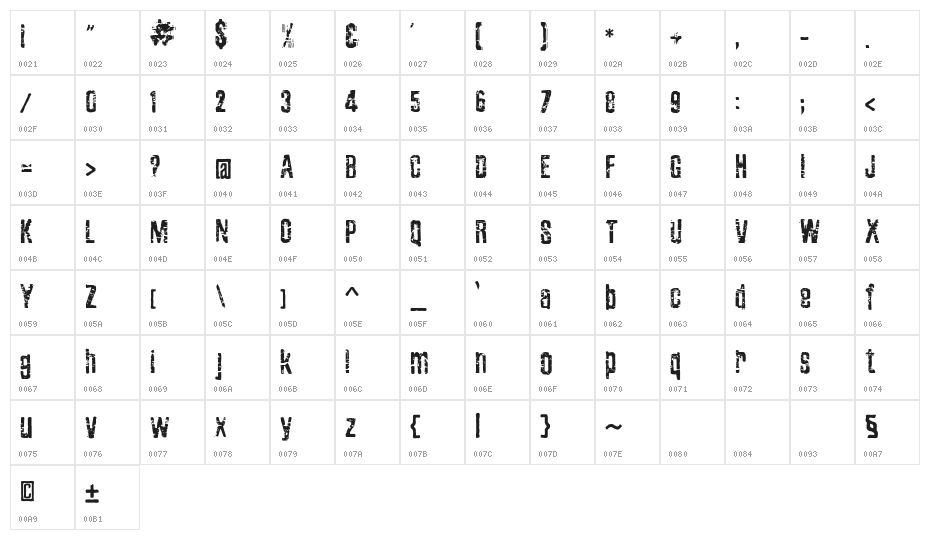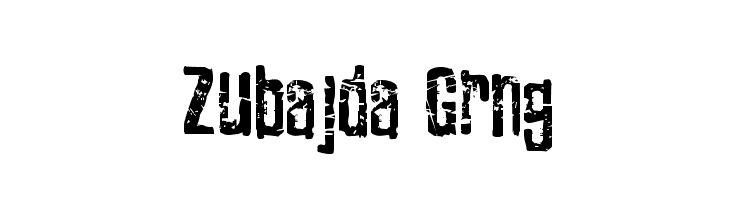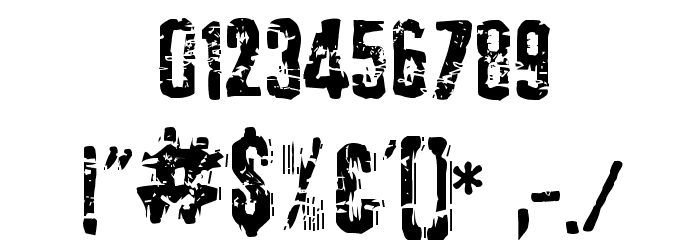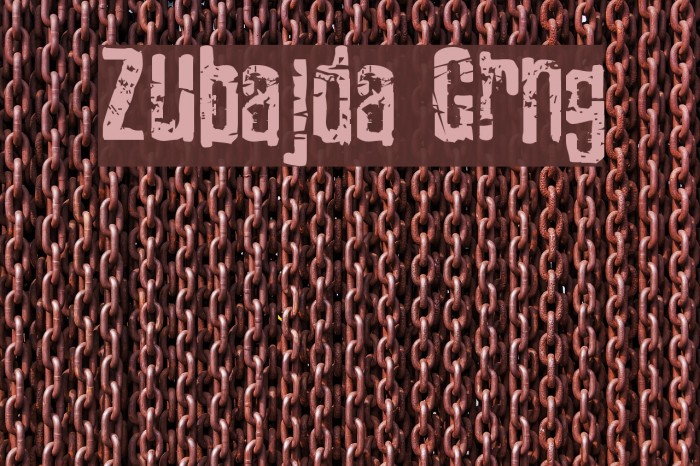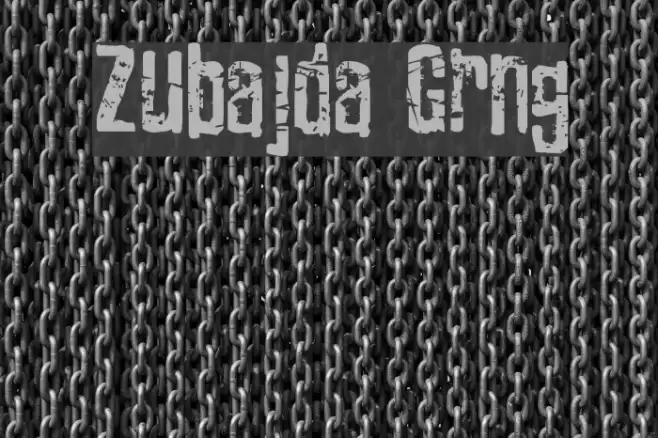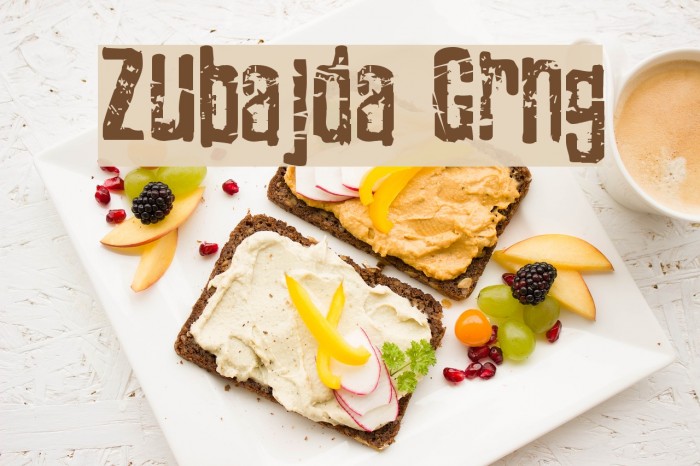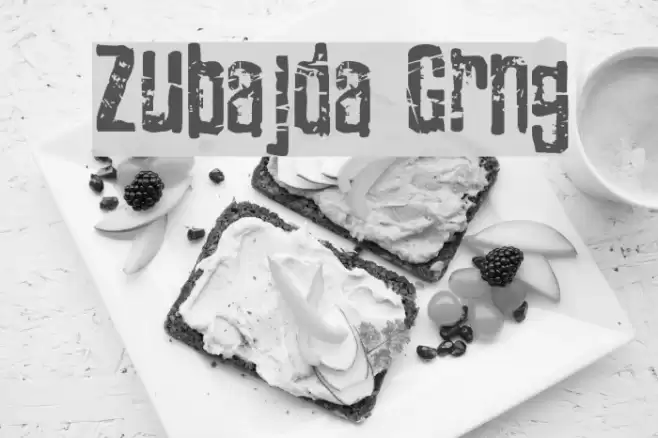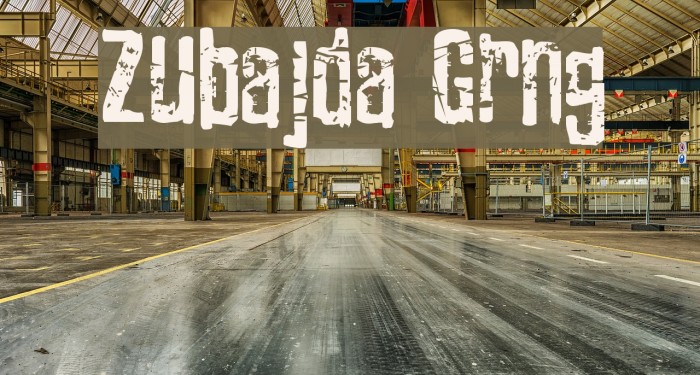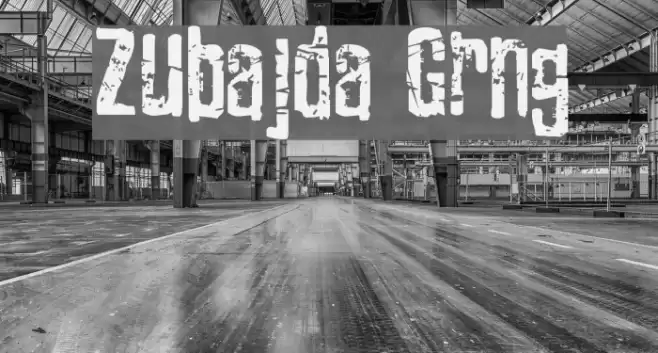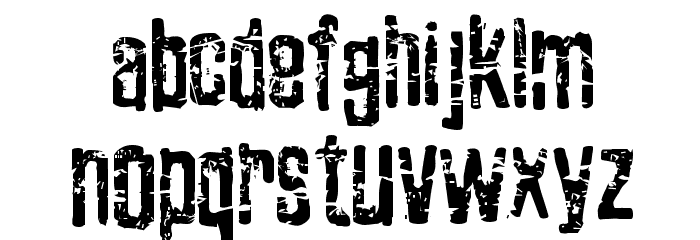
Zubajda Grng Font
✎ Distorted Eroded
| Categorii | Distorted Eroded |
| Stil general | Grunge, Vintage |
| Proiecte propuse | Ideal for music album covers, posters, urban-themed designs, and branding that requires a gritty, industrial look. |